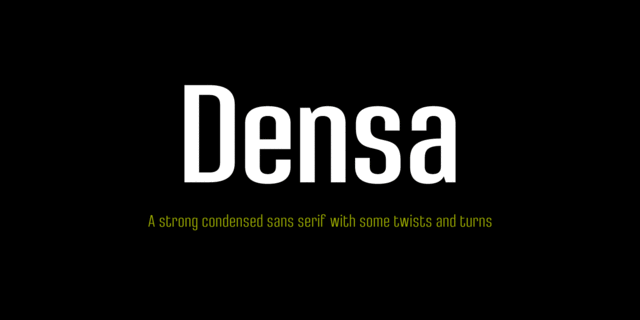
Это узкий гротеск с немного нетрадиционными окончаниями. Его компактный дизайн делает его очень эффективным для экономии места, а альтернативные формы букв делают его очень интересным вариантом для акциденции, например, логотипов, упаковки, плакатов. Шрифт был задуман как наиболее подходящий для заголовков и коротких текстовых блоков. Densa состоит из 8 начертаний. Каждое содержит капитель и символы для многих языков на латинице и кириллице. Шрифт разработал Пабло Балселлс в 2020 году.
Функции начертания Densa BoldПрименение в макете:
Ассоциации c начертанием Densa BoldКачества и характер:
громкий, важный, точный, ровный, убедительный, прямоугольный, стабильный, твердый, серьезный, надежный, уверенный, сильный, устойчивый, индустриальный, техногенный, деловой, статичный, мотивирующий, амбициозный, глобализированный, глобалистичный, ответственный, крутой, инженерный, чертежный, высокий, городской, спортивный, Ровный, взрослый, сжатый, заметный, монументальный, узкий, четкий, рабочий, солидный
политика, промышленность, техника, станок, инструмент, прибор, электростанция, энергетика, завод, тренажеры, бизнес, наука, дизайн, технологии, инженер, город, небоскреб, новости, рок-н-ролл, спорт, кинотеатр, стройматериалы, стройка, машиностроение, сырье, нефть, газ, недвижимость, архитектура, строительство, торговля, магазин, рабочий, селфи Стилистика: